かに沢のりおさんデザインのキュートな6書体が収録されています。
今回の日本語フォント集は第二弾です。第一弾の毛筆書体など8書体が収録されたフォント集も大好評で、デザインカッツ英語サイトの5周年イベント時には再販されました(こちらのフォント集の販売は終了しています)。
デザインカッツ「世界一可愛くてポップな日本語フォント集」の気になる中身
今回のフォントは全て縦書き・横書きに対応しています。前回の第一弾は縦書きに対応していないフォントも含まれていたので、縦書き対応は嬉しいですね。
恋みんちょう
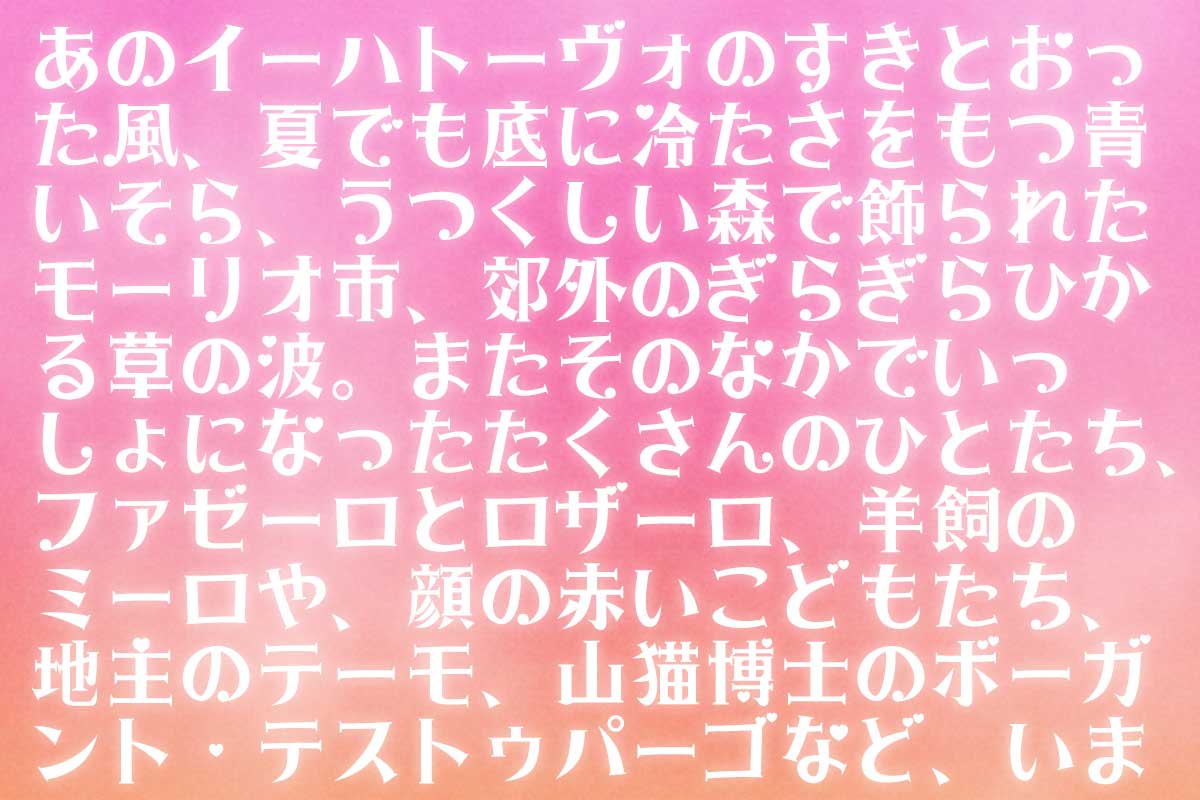
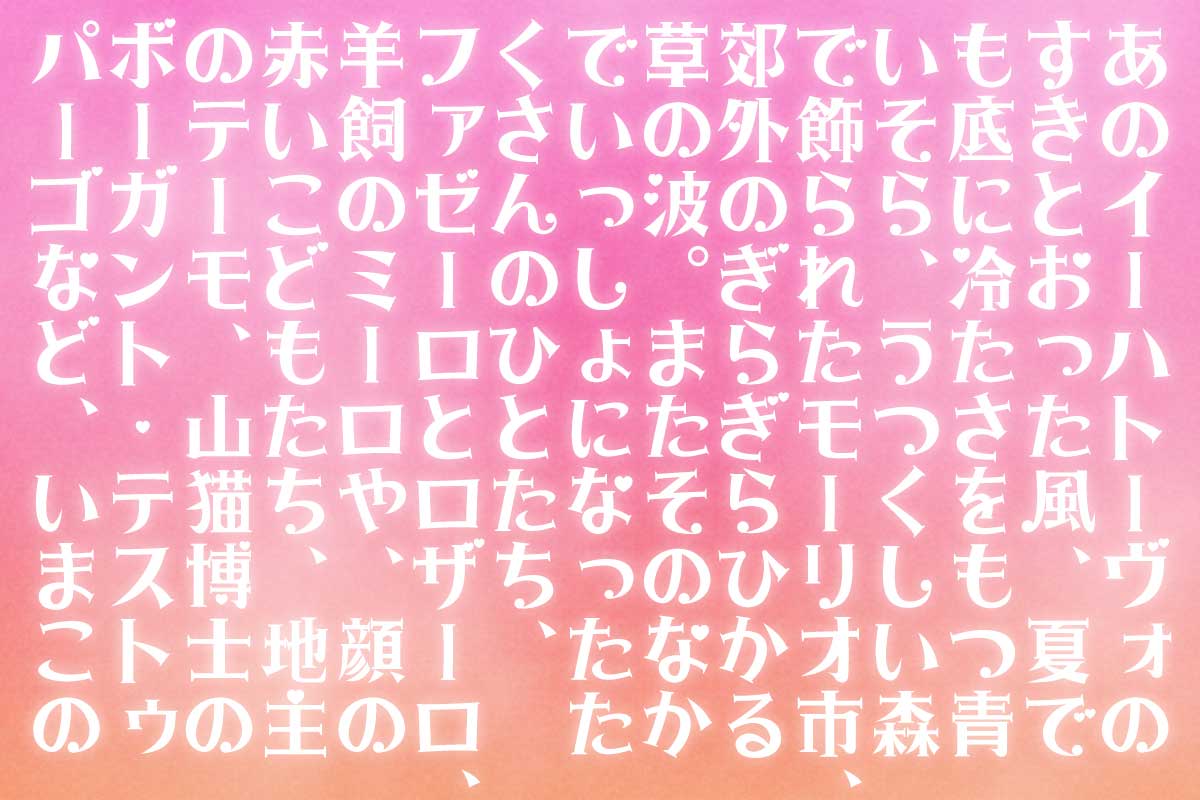
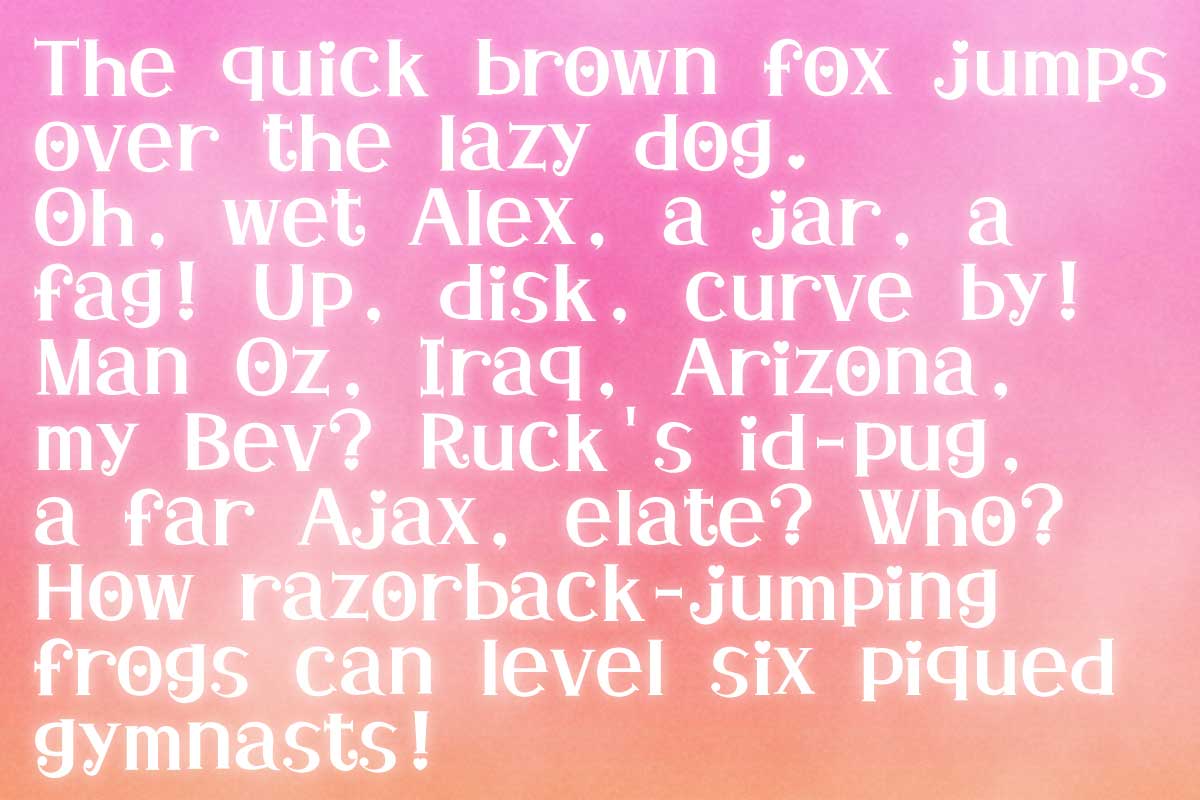
乙女みんちょう
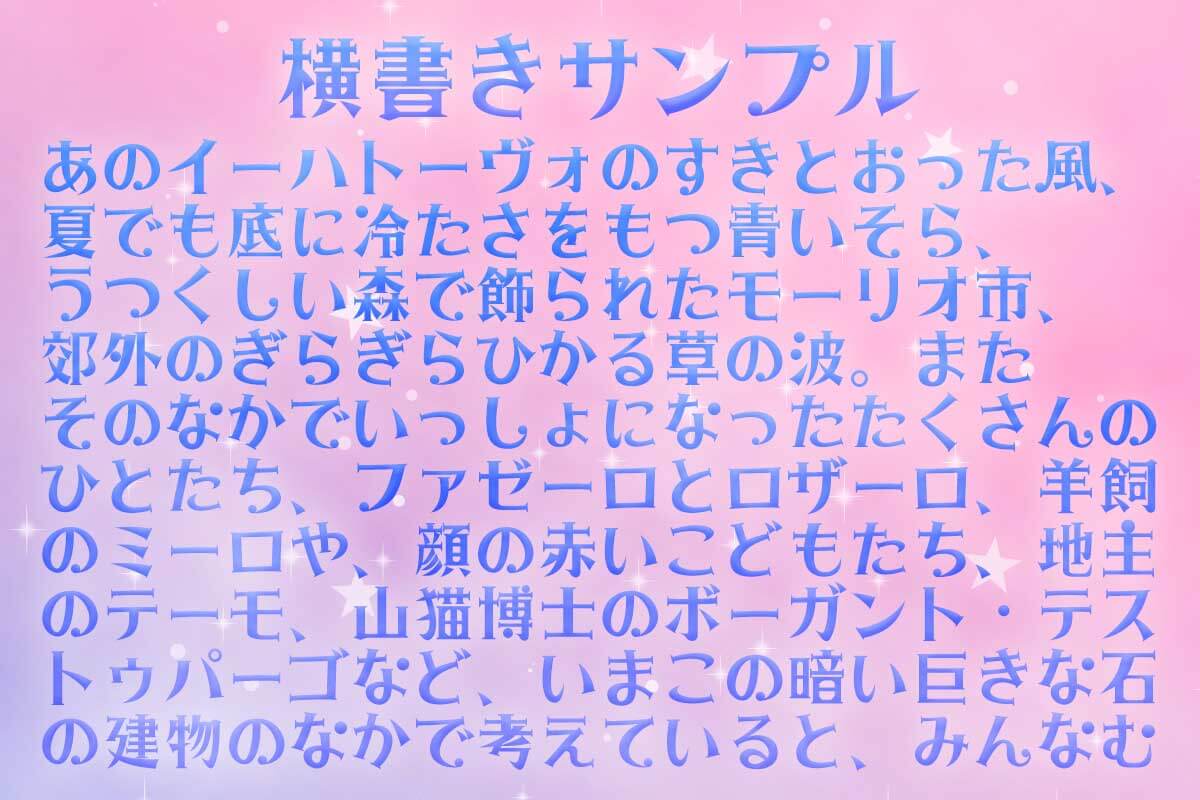
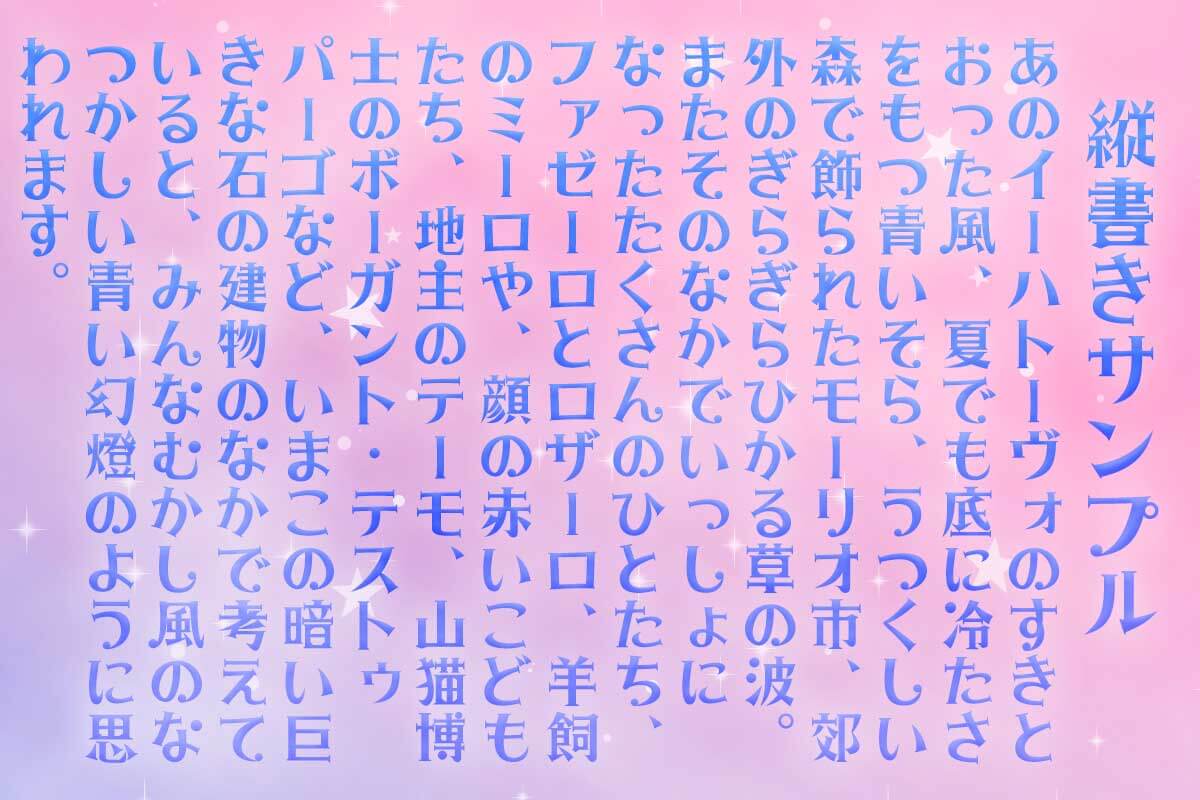
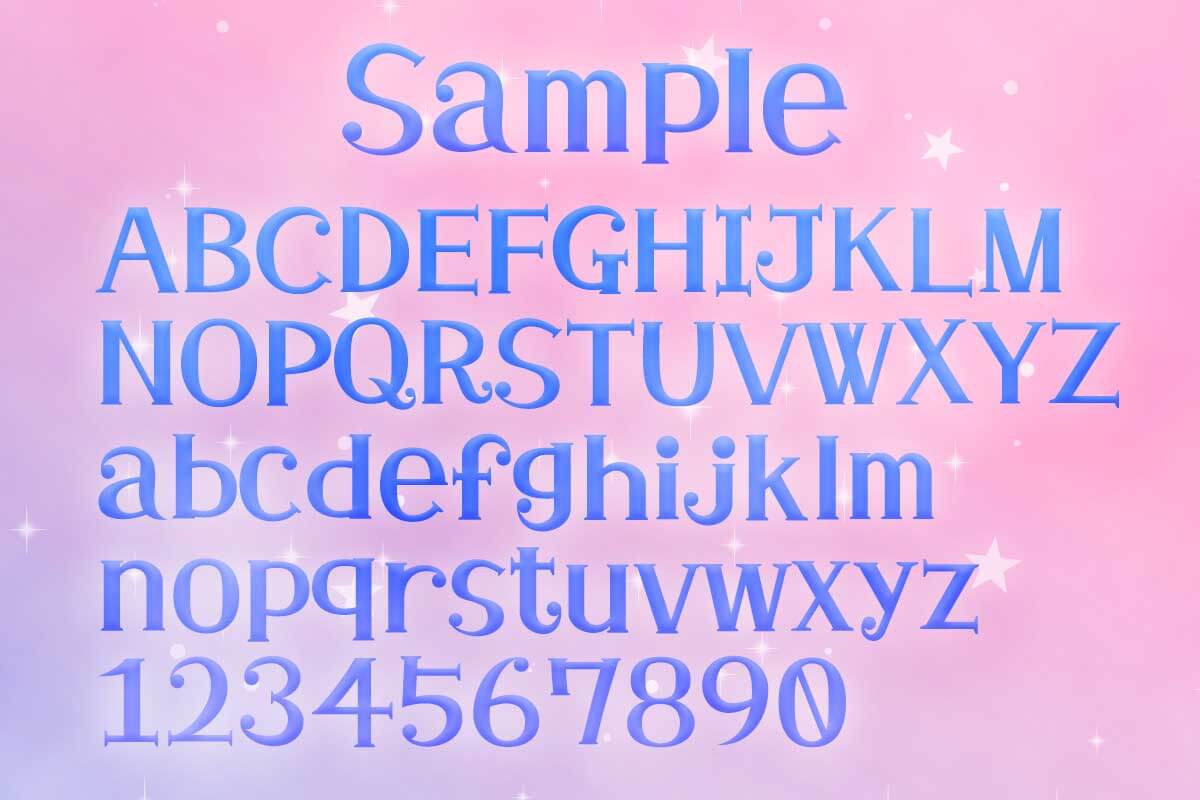
じゃんぴょんまる
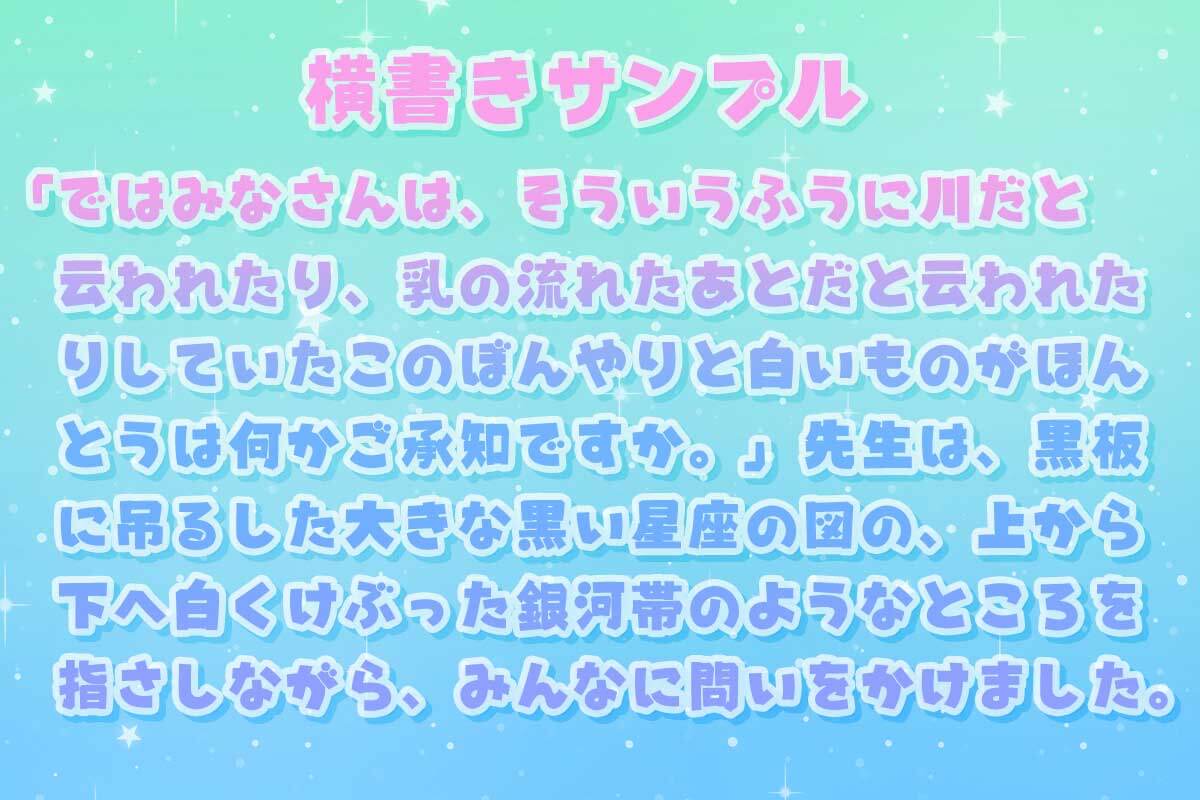
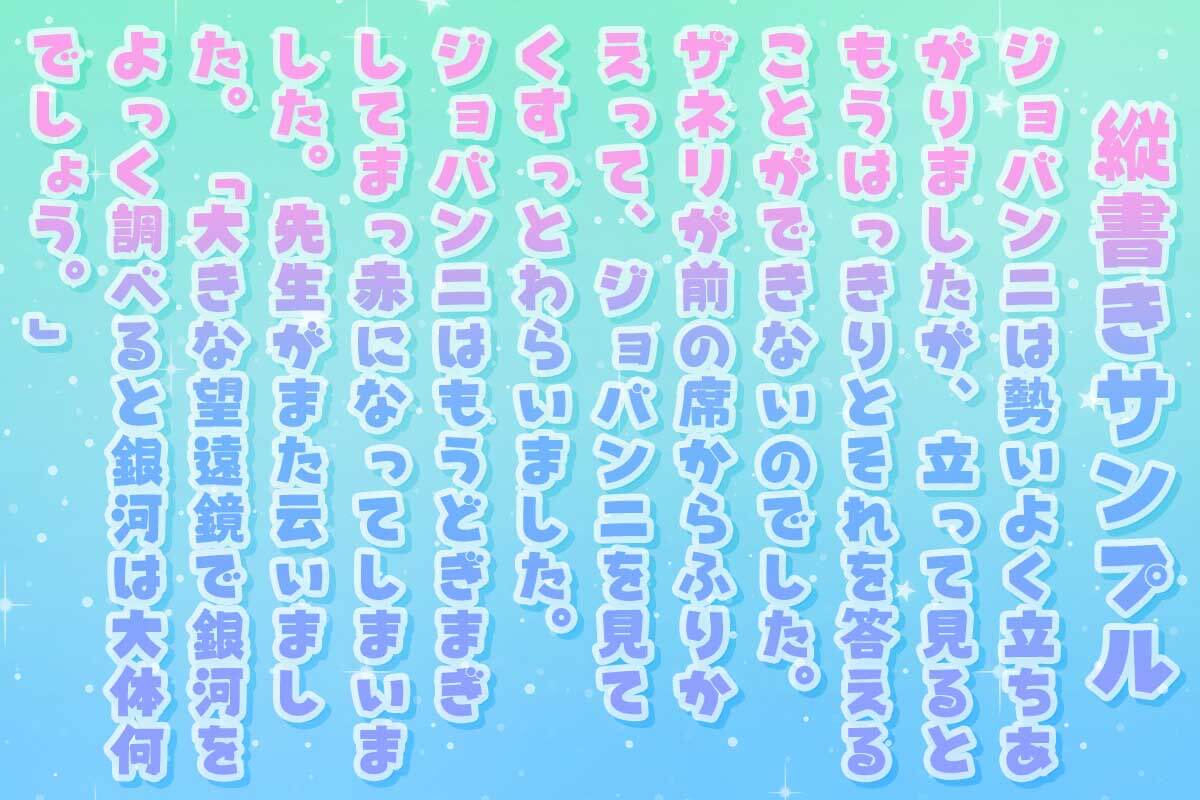
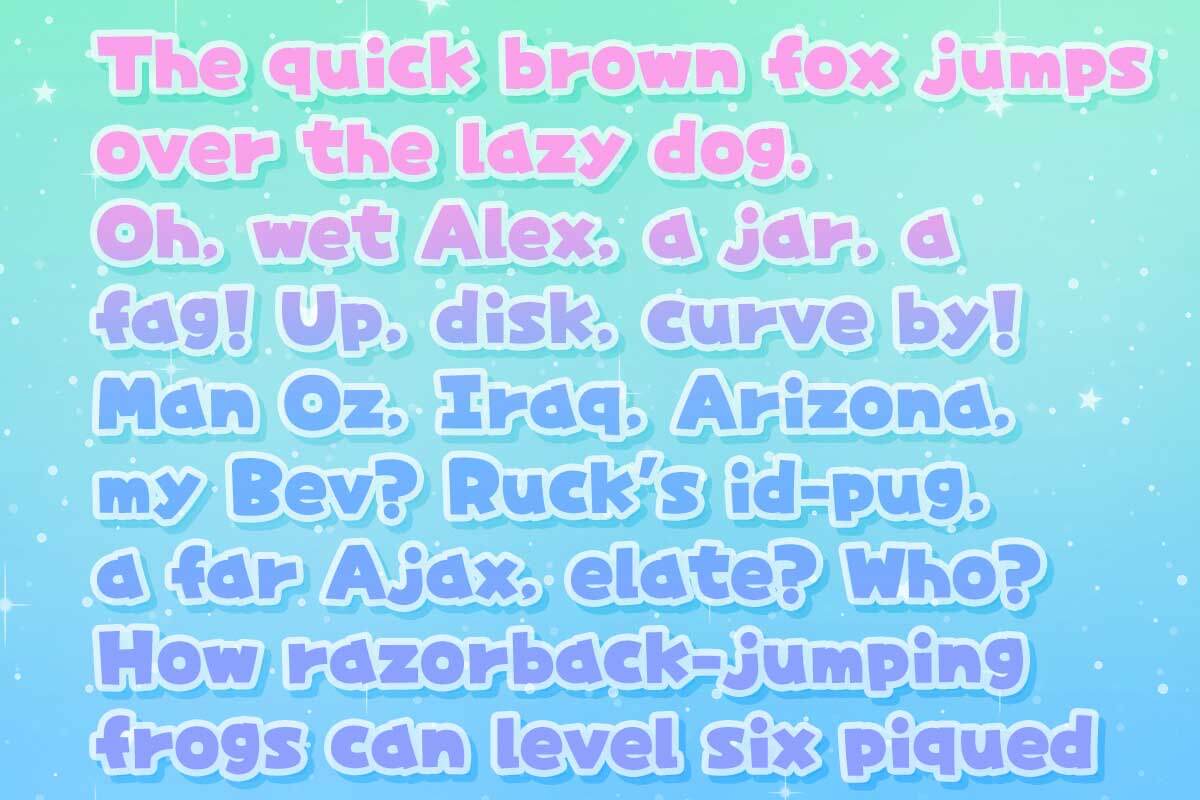
やんちゃポップ
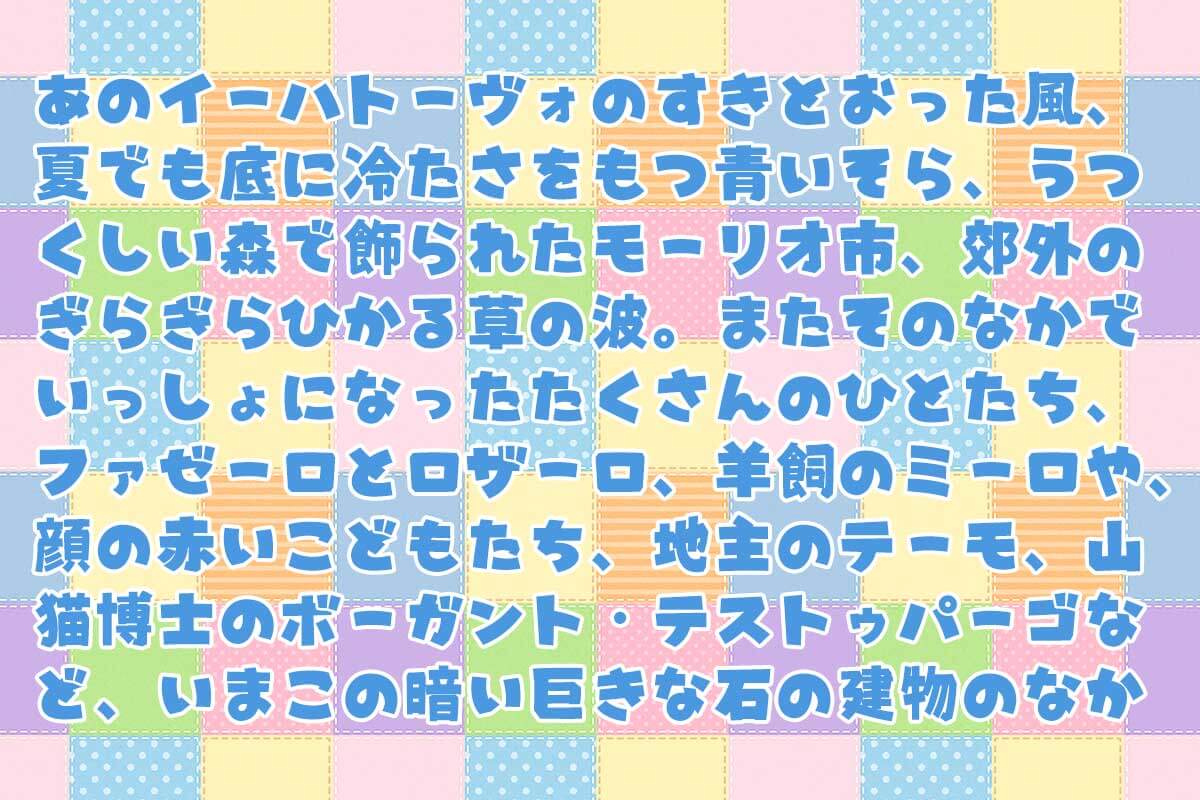
ちびすけふぉんと
なんと一万字以上の漢字(JIS第一・第二・第三・第四水準・IBM拡張漢字・人名用漢字)が使えます。
おてんばゴシック